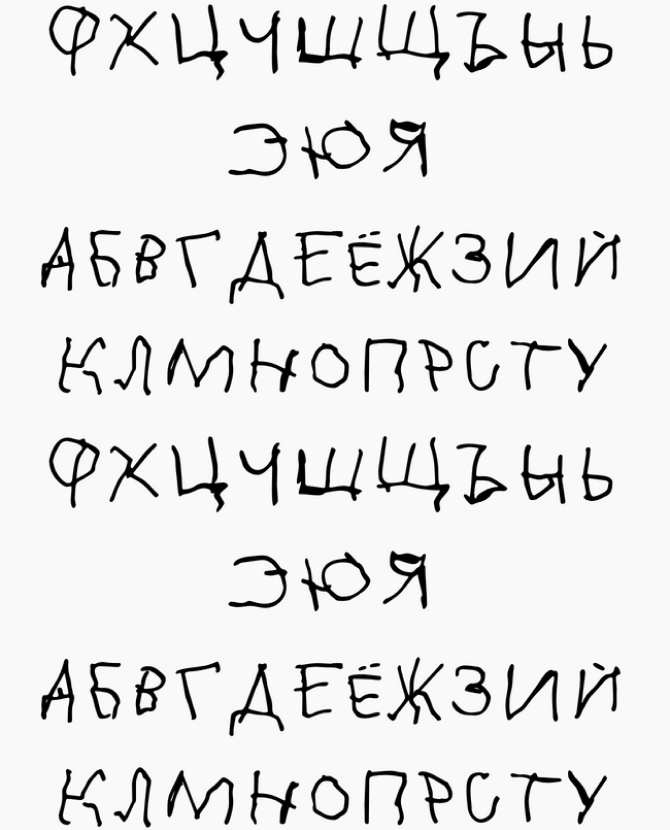
Дети с ДЦП нарисовали новый шрифт для логотипов «Яндекса», Lamoda и Ozon
Вы тоже можете скачать себе «Доброшрифт»
Сегодня в России проходит акция «Доброшрифт», приуроченная к Международному дню детского церебрального паралича. Ее запустили благотворительный фонд «Подарок ангелу» и рекламное агентство Smetana. Их цель — рассказать широкой аудитории о том, как сложно жить детям с церебральным параличом, и собрать средства на индивидуальные программы по реабилитации детей и помощь их семьям.
В рамках проекта дети с ДЦП создали специальный шрифт, который был использован для новых логотипов крупных российских компаний и организаций, среди которых — «Яндекс», футбольный клуб «Зенит», сеть магазинов «Лента», «Почта России», онлайн-ритейлеры Lamoda и Ozon. На сайте инициативы вы можете прочитать истории детей, которые приняли участие в работе над шрифтом, скачать его и сделать пожертвование.